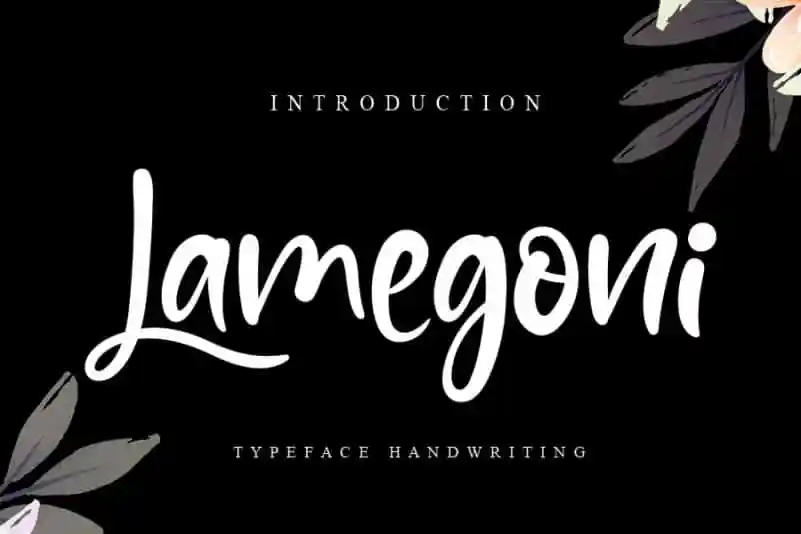
Lamegoni Script Font – Download Grátis
A Lamegoni Script Font é inspirada na tipografia clássica e traz seu próprio estilo único a qualquer projeto de design. Seja para web, impressão ou vídeos em movimento, esta fonte irá brilhar. Perfeita para aqueles buscando um toque personalizado em seus projetos gráficos, a Lamegoni Script oferece uma versatilidade que se adapta a todos os tipos de mídia. Seja você um designer web, criativo ou editor de vídeos, essa fonte trará seu trabalho à vida com um ar sofisticado e elegante, adaptando-se facilmente às suas necessidades específicas. A Lamegoni Script é a escolha perfeita para aqueles que buscam personalidade em cada projeto.